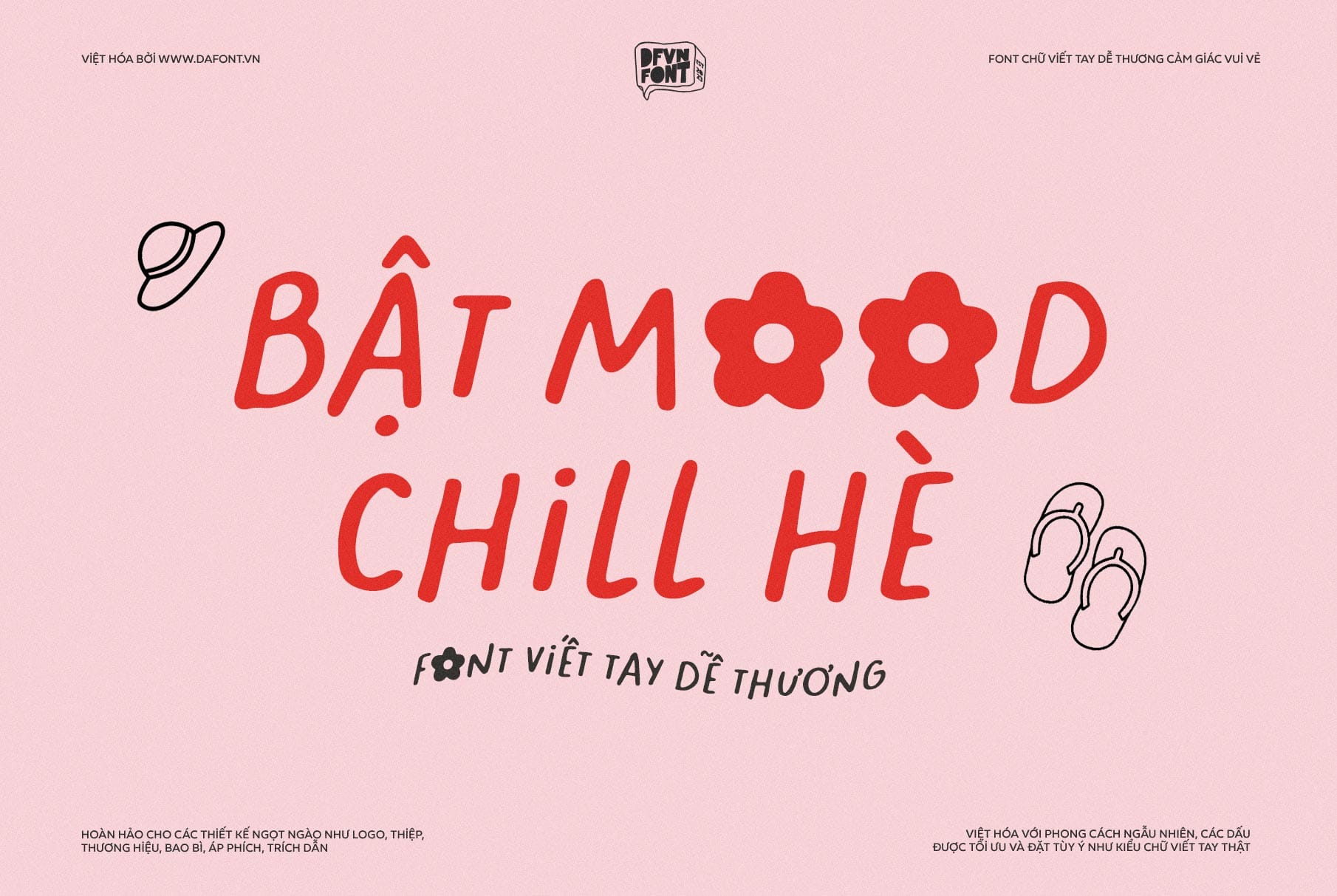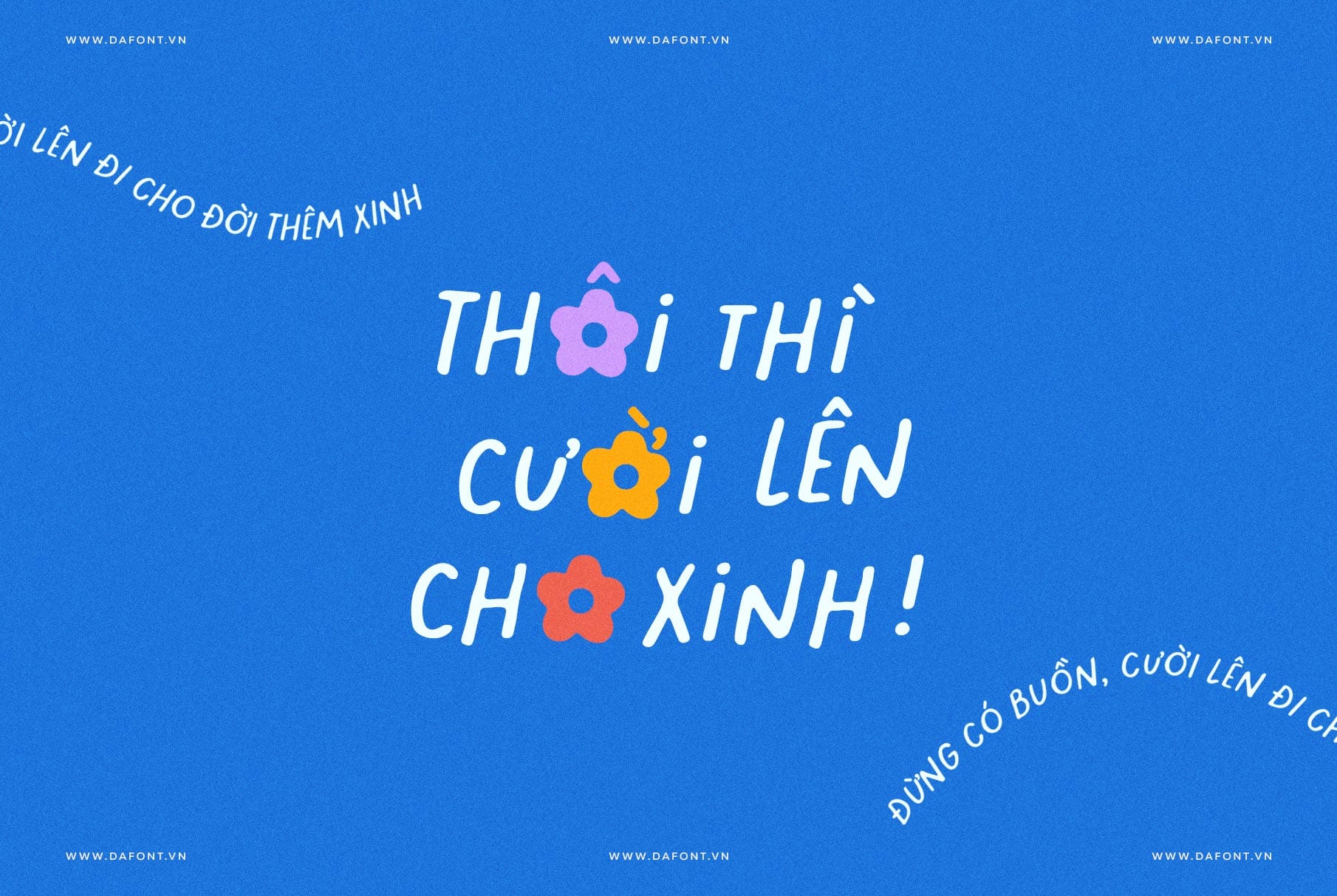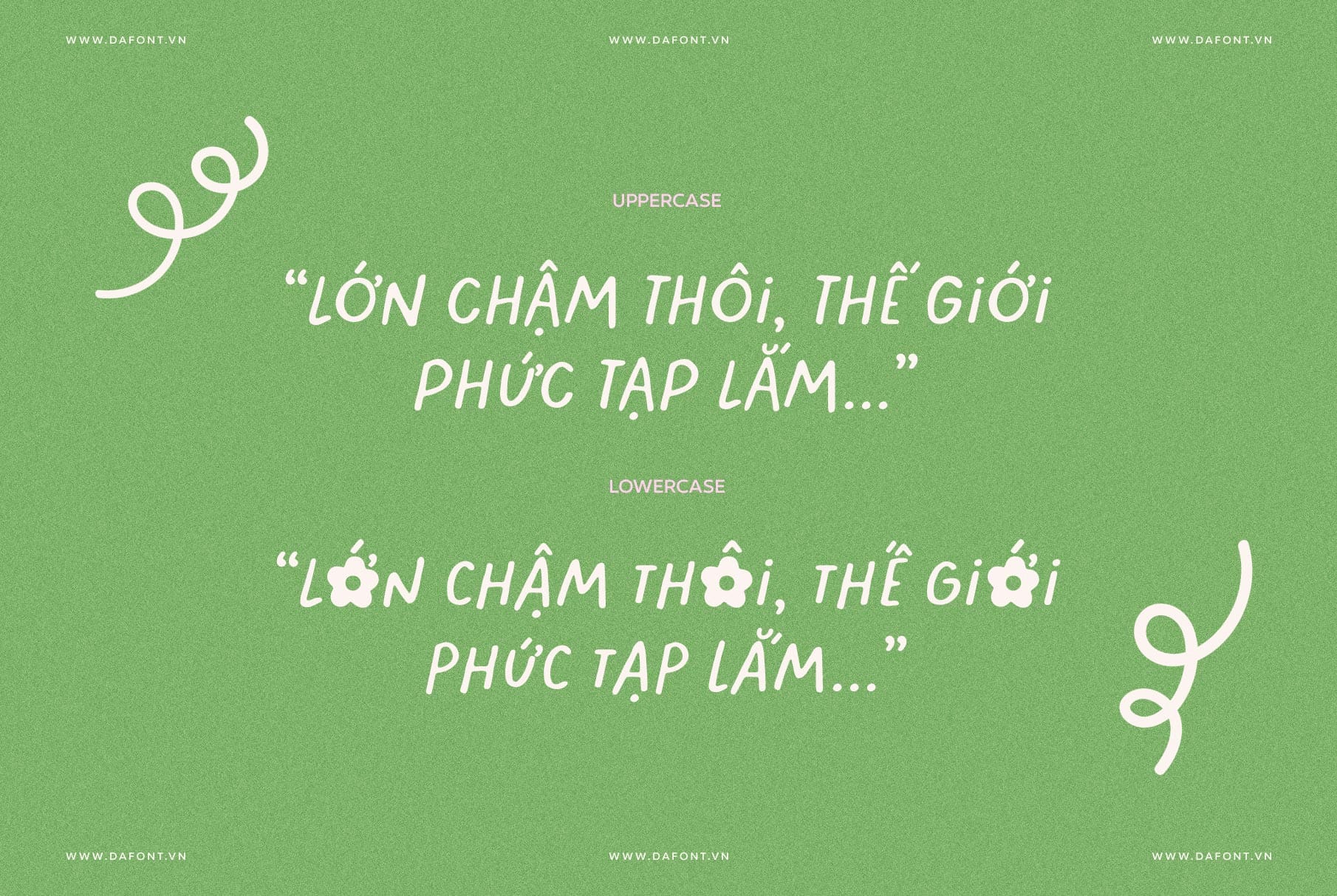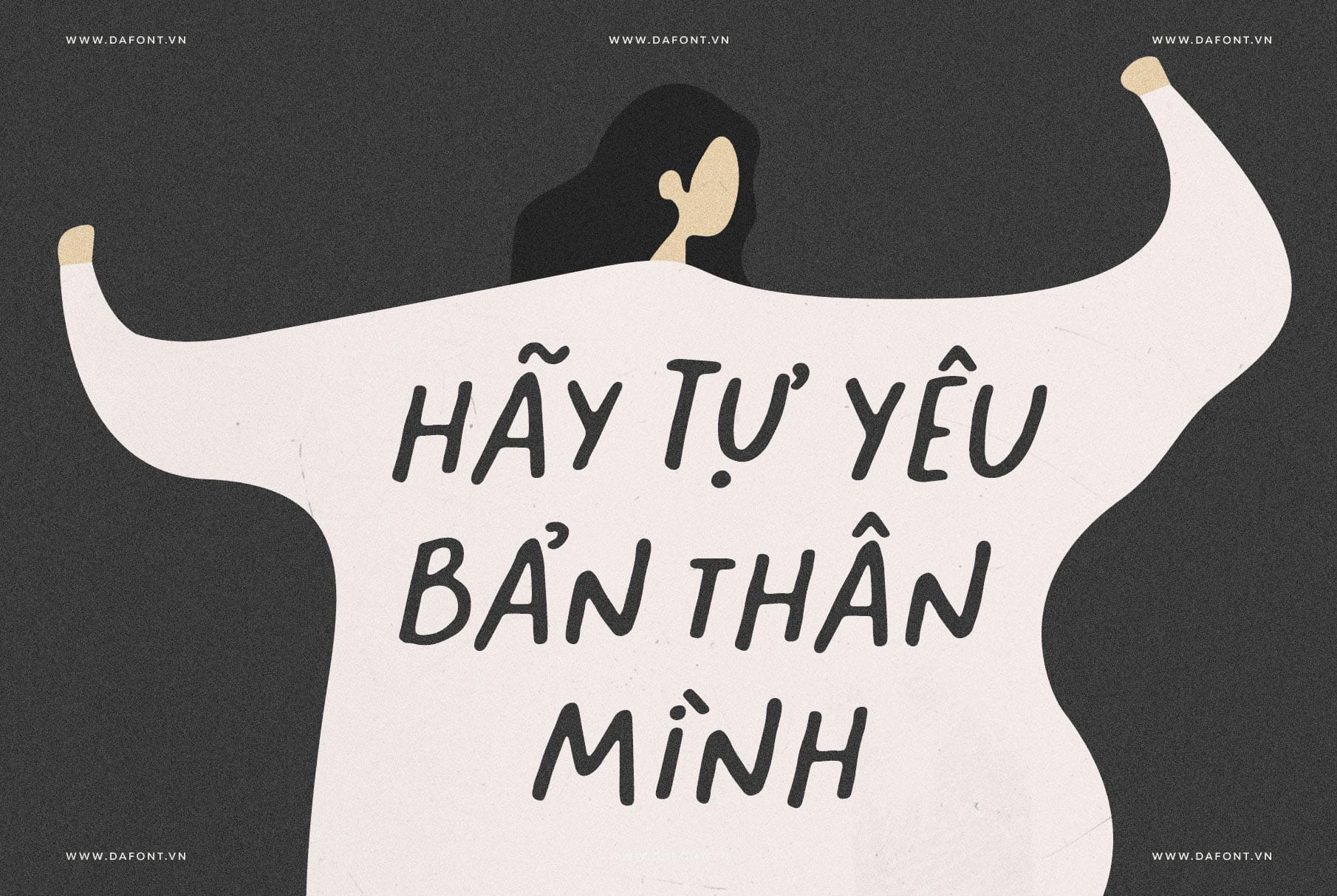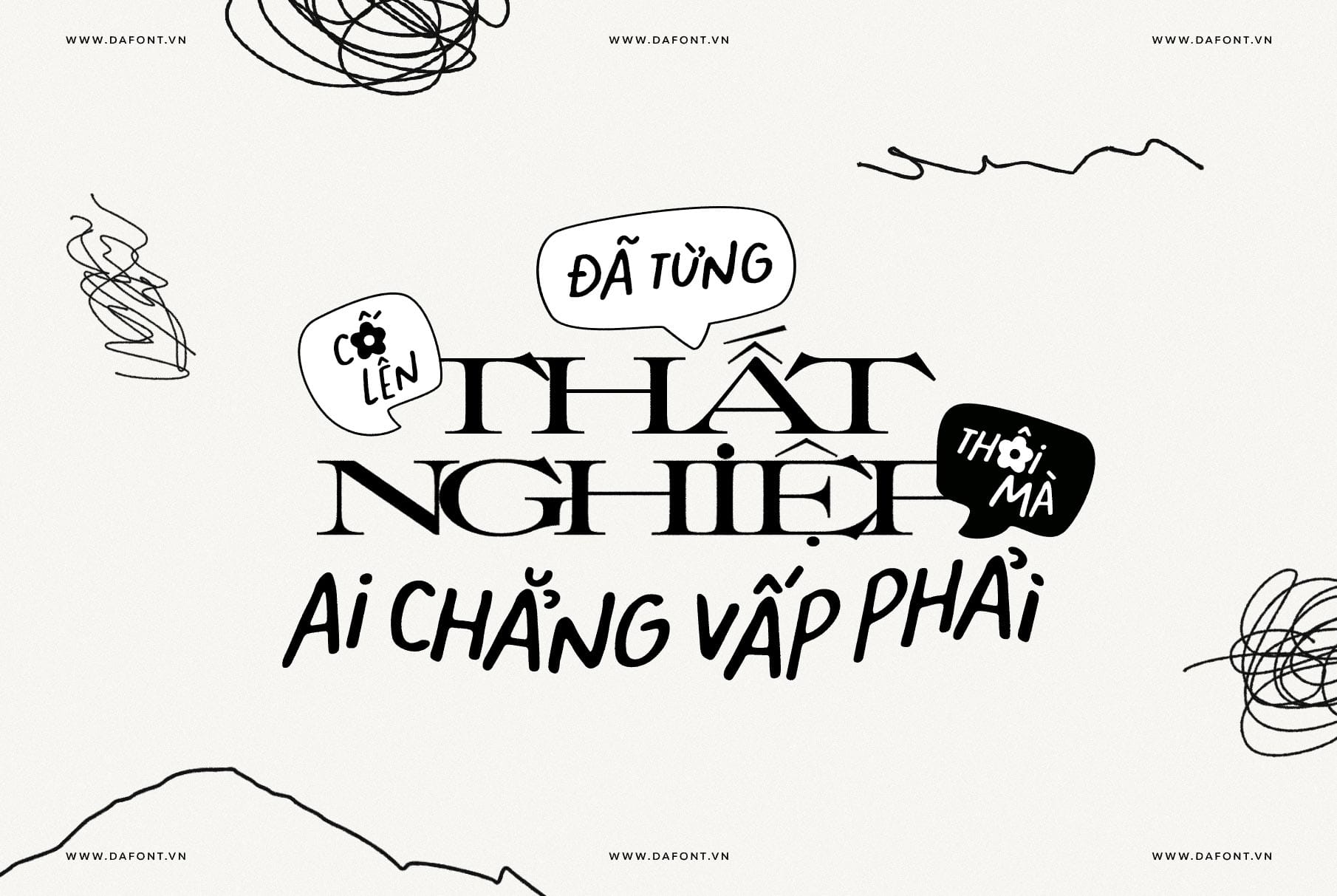
Bạn đang tìm kiếm một font chữ độc đáo để làm nổi bật các dự án thiết kế của mình? DFVN Blooming Mood là một font chữ viết tay dễ thương, mang phong cách vui vẻ và trẻ trung, lấy cảm hứng từ những ngày hè rực rỡ, lý tưởng để tạo nên những thiết kế tươi mới và thu hút.
Đặc điểm nổi bật của DFVN Blooming Mood
Blooming Mood nổi bật với nét chữ thủ công mềm mại, cùng đường cong uyển chuyển, mang đậm tinh thần “summer vibes” tươi sáng và vui vẻ. Với phong cách viết tay “cute” không chỉ tạo điểm nhấn cá tính mà còn lan tỏa cảm giác vui tươi, lạc quan cho mọi dự án thiết kế.
- Phong cách viết tay tự nhiên: Nét chữ mềm mại, uyển chuyển, tạo cảm giác gần gũi và thân thiện với người xem.
- Vibes mùa hè: Font mang đến cảm giác tươi mới, rực rỡ, rất phù hợp cho các thiết kế lấy cảm hứng từ mùa hè hoặc chủ đề vui tươi, trẻ trung.
- Ứng dụng đa dạng: Blooming Mood thích hợp cho thiết kế logo, nhận diện thương hiệu, bao bì sản phẩm, áo thun, thiệp, poster, trích dẫn, bài đăng mạng xã hội, sticker và nhiều ứng dụng sáng tạo khác.
- Phiên bản Việt hóa độc đáo: Blooming Mood đã được Việt hóa, hỗ trợ đầy đủ các ký tự tiếng Việt, các dấu được tối ưu và đặt tùy ý giống như chữ viết tay thật.
DFVN Blooming Mood là một font chữ vô cùng linh hoạt, phù hợp với nhiều phong cách và lĩnh vực thiết kế: từ bộ nhận diện thương hiệu, logo, bao bì sản phẩm cho đến thiệp mời, greeting card và ấn phẩm mạng xã hội. Với nét vẽ tay mềm mại, chân thực. Blooming Mood dễ dàng sử dụng cho nhiều thiết kế khác nhau, mang đến sự đồng nhất nhưng vẫn giữ cá tính riêng cho dự án của bạn.
Blooming Mood – Font viết tay độc đáo
Dù bạn đang xây dựng thương hiệu tươi trẻ hay muốn làm nổi bật bài đăng trên mạng xã hội, DFVN Blooming Mood sẽ mang đến phong cách thân thiện, đậm chất mùa hè. Với thiết kế thủ công độc đáo và cách dùng dễ dàng, đây chắc chắn là lựa chọn hoàn hảo cho mọi designer yêu thích sự nhẹ nhàng, vui tươi.